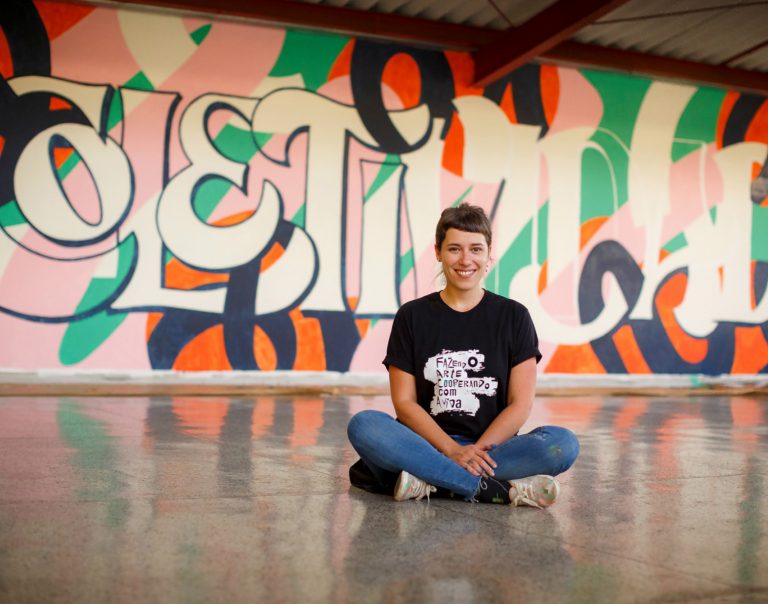
MUJERES EN TIPOGRAFÍA: CYLA COSTA
En esta quinta entrega de la serie que en Rayitas Azules estamos dedicando a mujeres latinoamericanas que desarrollan su carrera profesional en el universo de la tipografía nos vamos a Curitiba, capital del estado de Paraná, al sur de Brasil, para encontrarnos con Cyla Costa.
Artista gráfica
No hay más que echar un ojeada a su web: la versatilidad de Cyla Costa es abrumadora. Diseñadora gráfica, letrista, ilustradora, muralista, portadista…todo ello atravesado por el espíritu de las letras. Una versatilidad y una impronta que la han llevado a colaborar con marcas como Google, Coca-Cola o Penguin Ramdon House.
La soltura y naturalidad con que maneja sus herramientas, tanto físicas como conceptuales, le permite pasar de la pequeña escala, el papel, la pantalla o, incluso, la letra bordada con aguja e hilo, a la gran escala de la pared para crear murales en los que la letra ilustrada alcanza su apogeo estético como sustrato de su faceta más activista.
En el caso de Cyla sí que se puede afirmar que la (presunta) frontera entre diseñadora y artista ha saltado felizmente por los aires. Su trabajo abarca prácticamente todos los ámbitos de la comunicación gráfica y, quizá por su profundización en técnicas manuales y su empeño por bucear en lenguajes visuales diversos, posee la capacidad de adaptarse a cada proyecto o medio con maravillosa solvencia. «Soy una artista gráfica brasileña que siempre tuvo un amor especial por el mundo de las formas de las letras. Después de terminar la universidad, viví un tiempo en Barcelona, donde estudié ilustración creativa y diseño editorial con un enfoque en la tipografía. Al volver a Brasil, me gusta pensar que combiné estas habilidades, lo que me llevó naturalmente a la tipografía, el lettering y la caligrafía.»
Cultura brasileña, cultura global
Cyla Costa reside y trabaja en Curitiba, su ciudad natal, y en su estilo late la vibrante y luminosa cultura brasileña. Pero, tras formarse en ciudades como Barcelona y Nueva York, en primer lugar tuvo claro que «el camino a seguir para mí sería desarrollar mi propia carrera como freelance y por suerte tuve el apoyo para hacerlo. Empecé a acercarme a la profesión acudiendo a eventos relacionados con la tipografía siempre que tenía la oportunidad, conociendo a gente inspiradora, tomando sus talleres y practicando mucho. Pronto empecé a ofrecer mis servicios como artista tipográfica antes de tener la suficiente confianza, y me parece que fue genial porque crecí mucho mientras aceptaba los retos que cada proyecto traía».
Diversos murales creados por Cyla Costa
Proyecto Saudade. Proyecto organizado por @ladieswhopaint
Gesto y esencia de la letra
Llama poderosamente la atención la naturalidad que emana de los trabajos de Cyla Costa. Lo hemos recalcado más arriba. Quizá sea cierto que hay personas dotadas de especial talento para ciertas labores, aunque no hay duda de que la dedicación metódica y constante es la que hace verdaderamente firmes los cimientos de todo lo que vendrá después. La naturalidad se consigue no dejando nunca de reforzar estos cimientos. Intentando mantenerse fiel a ese impulso innato que lleva a niñas y niños a una pureza creativa que resulta prácticamente imposible de mantener con los años, pero que, en algunos casos, pervive en cierto modo latente, y cuando esto sucede es una fiesta para los sentidos.
Wolf Hall series books
Mujercitas para Penguin Random House
En el trabajo de Cyla se puede percibir ese impulso natural en el gesto que es capaz de aflorar la esencia de las formas de las letras. Como ella misma reconoce, su acercamiento profesional al universo lettering, la caligrafía y la tipografía «surgió de forma natural después de las experiencias que tuve con mis estudios y mi trabajo. No tenía experiencia en esto específicamente, así que empecé a tomar talleres y a estudiar en línea todo lo que podía, yendo a eventos y a ponerme en marcha como artista de lettering freelance. En 2014 tuve la oportunidad de pasar el año en NYC, donde pude profundizar en el universo tipográfico asistiendo a un curso en la Cooper Union y teniendo acceso a sus charlas y premisas. En esta época empecé mi estudio propio, que ha cambiado con los años, pero cuya esencia sigue siendo la misma: un estudio de una sola mujer que explora técnicas e ideas en la escritura y el dibujo de letras, con la esperanza de comunicarse con su público».
La bendita trinidad
Tipografía, caligrafía y lettering son los tres lados de un triángulo infinito. No hay un camino predeterminado, cada cual encuentra su propia senda a través de la cual desarrollar sus inquietudes e intereses creativos. «Mi trabajo ha sido siempre ha sido con el lettering y algo de caligrafía, no como calígrafa tradicional sino utilizándola para que me aporte las buenas formas que uso para dibujar mis palabras.
Google Allo Stickers
La tipografía ha sido un campo más, aunque la estudié en NYC y siempre estoy leyendo y viendo charlas sobre lo que está pasando. Creo que estoy entrando en una fase de mi vida en la que me atrae la tipografía y me interesa diseñar mis propias tipos de letra con todo lo que está pasando. El panorama que estamos viviendo ahora mismo es muy apasionante con el auge de las fuentes variables y otras mejoras técnicas que acercan la tipografía a la gente y facilitan su uso.
Mi sueño sería fundar o cofundar una fundición tipográfica de mujeres con el increíble trabajo que ellas están haciendo actualmente.»
Virtude Cênica
Weekly Woody
Aprender, crear, enseñar
Por lo tanto, para espíritus aventureros, la relación con las distintas vertientes de las formas de las letras es necesariamente cambiante, mutante, se enriquece a cada paso, a cada nuevo aprendizaje, proyecto o experiencia. «Ahora mismo estoy trabajando en el desarrollo de un curso online (que espero sea el primero de muchos) y esto me está haciendo pensar mucho en mi proceso y estoy estudiando tantas cosas nuevas, además de las ya estudiadas, para poder enseñar mejor a mis alumnos.
Nuevo curso online de Domestika de Cyla Costa
Estoy también trabajando en una línea de productos para el hogar a través de una colaboración con una empresa de papel pintado, así que puedo llegar a un público más amplio con mi arte. Aparte de esto, intento mantener el equilibrio entre el trabajo por encargo, el personal y el activista, porque trabajar con cosas en las que creo es realmente importante para mi salud mental. En cuanto al lenguaje y la técnica, siempre estoy pensando en cómo ser una mejor artista y explorar nuevos territorios que sean significativos para mí y para los demás.»
Fer Cozzi, Cyla Costa Y Yani Arabena
Mural Fuerza Hermana para Centro Cultural Recoleta